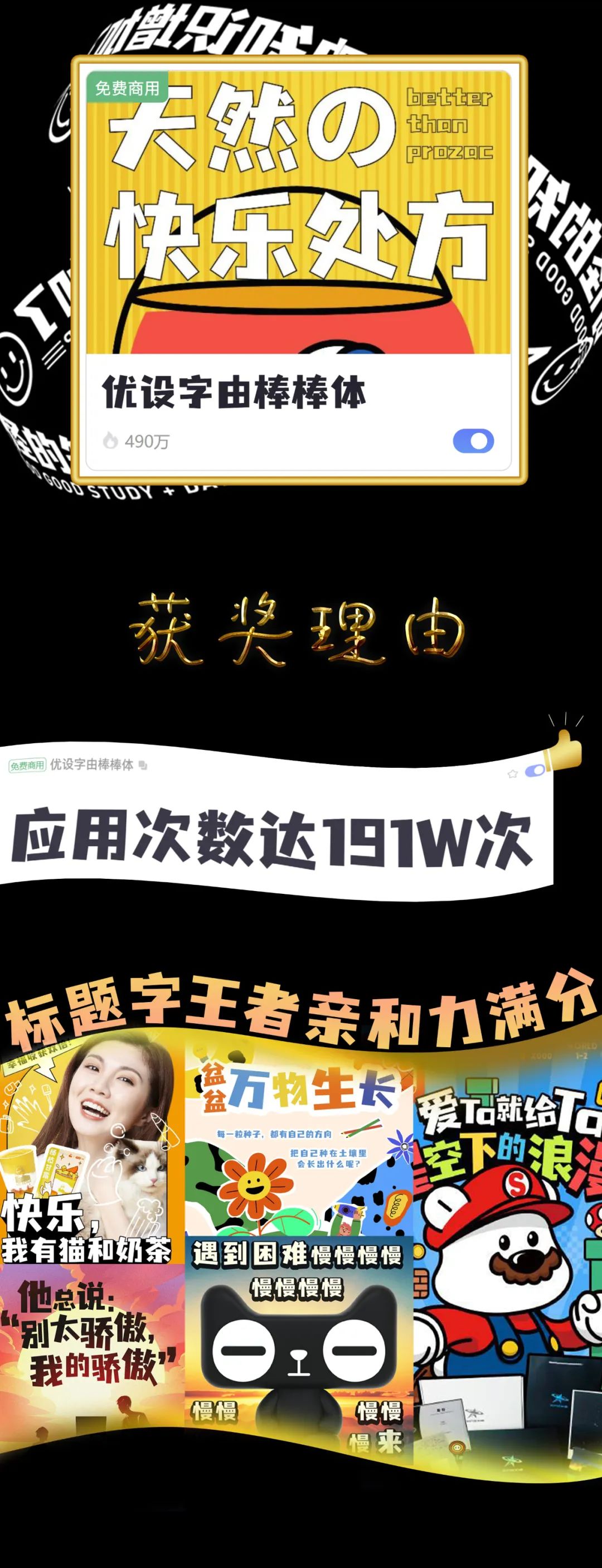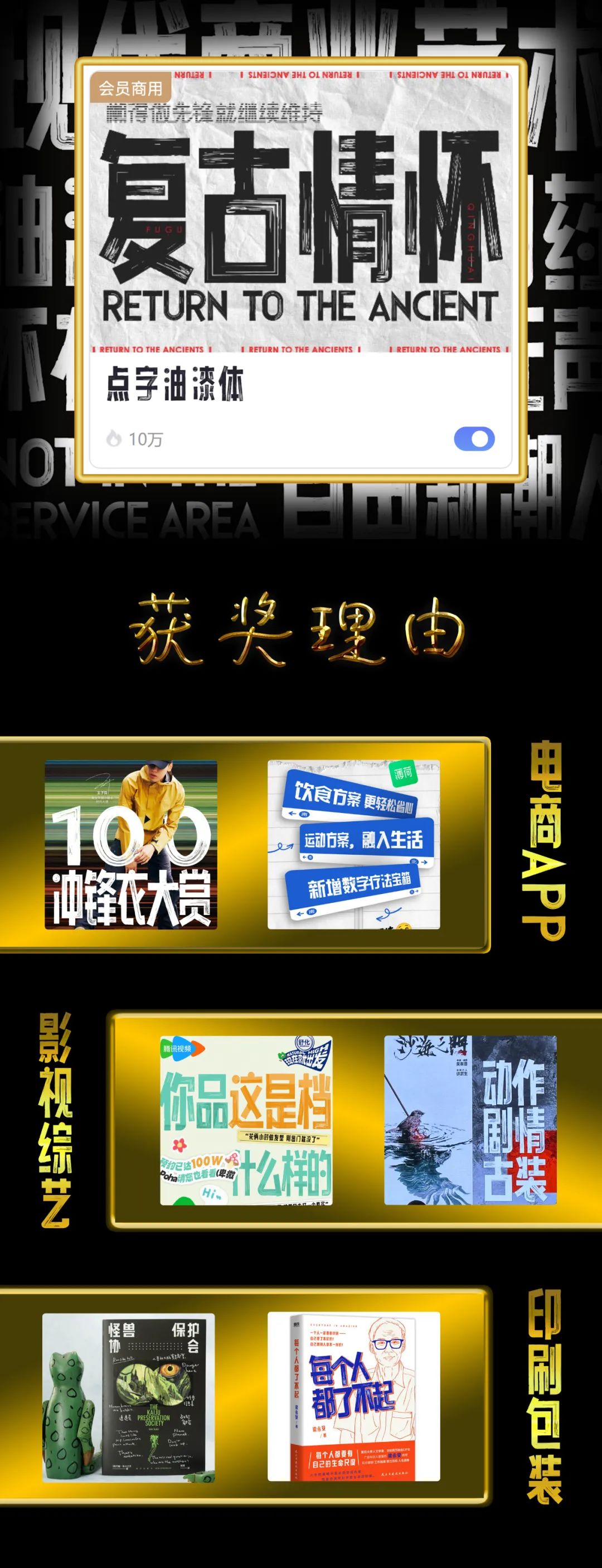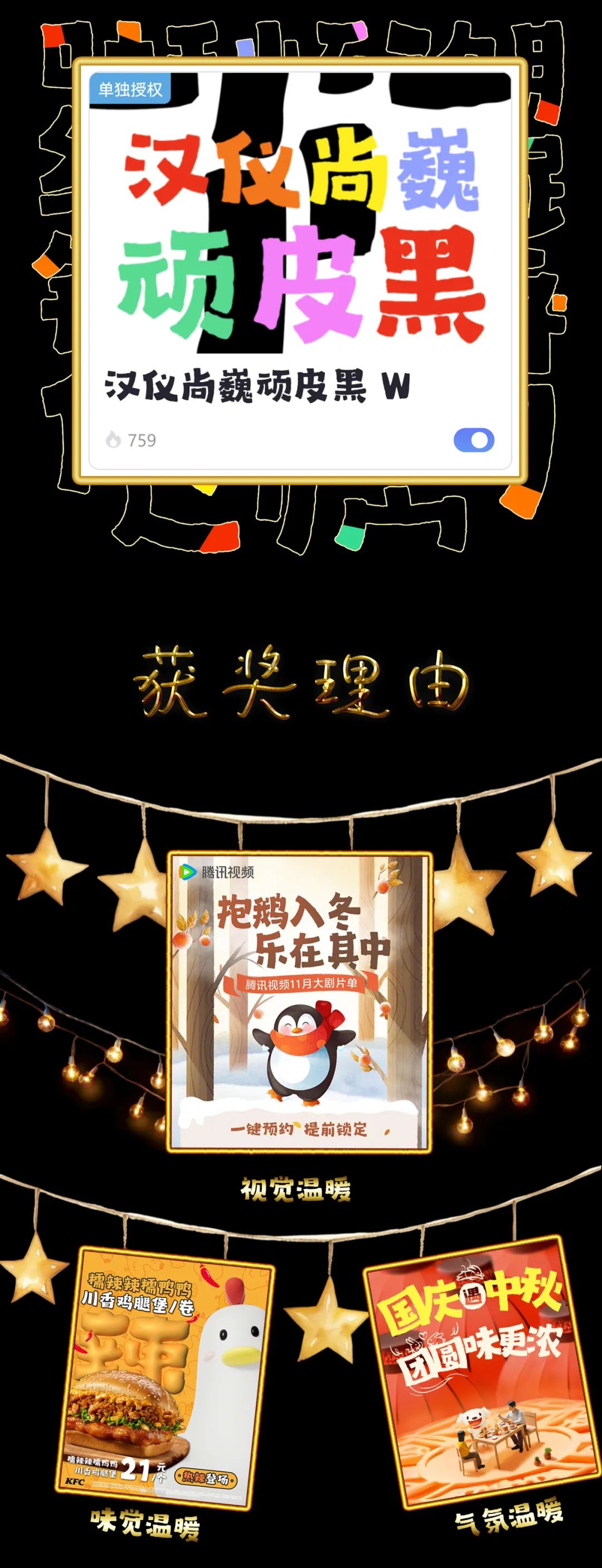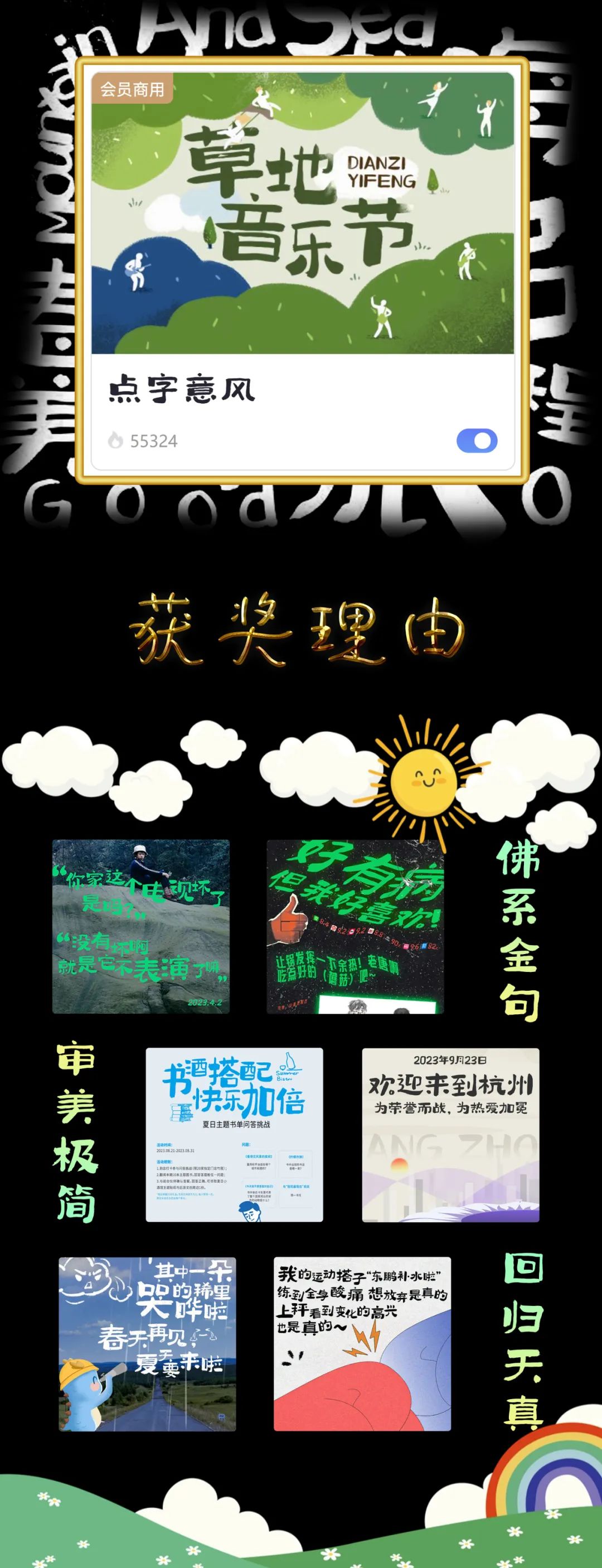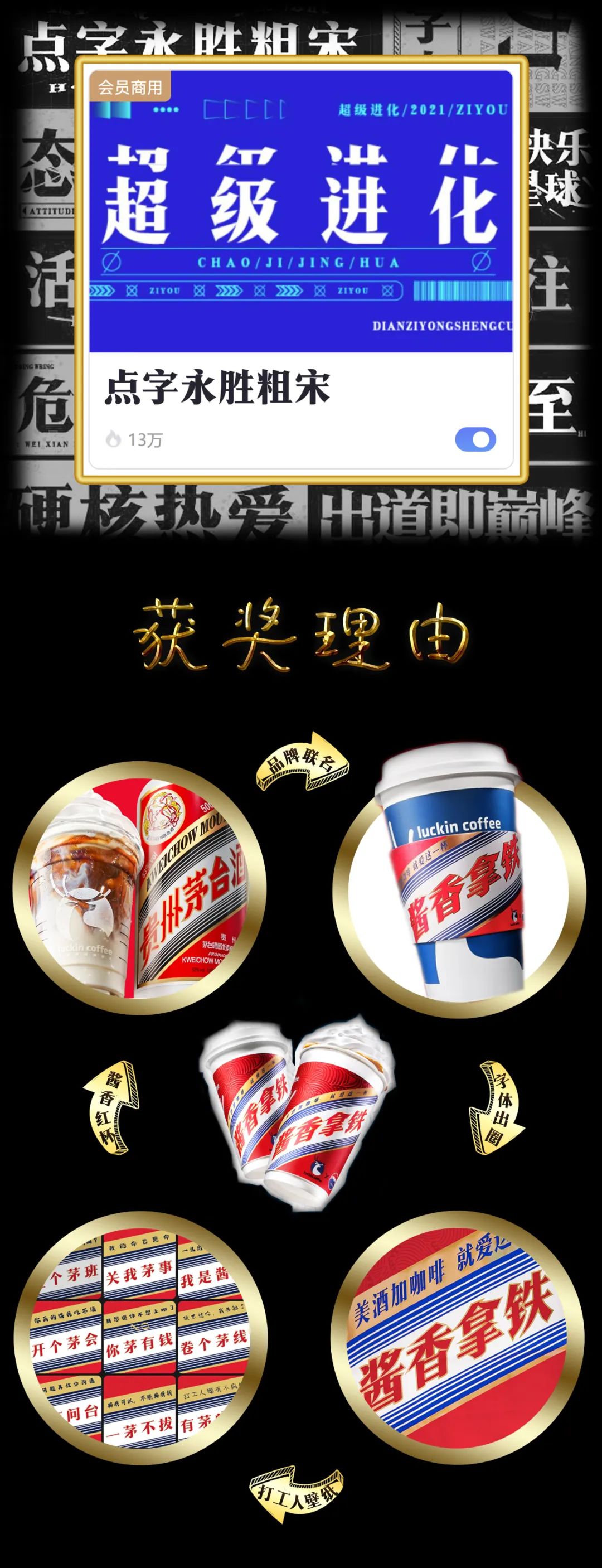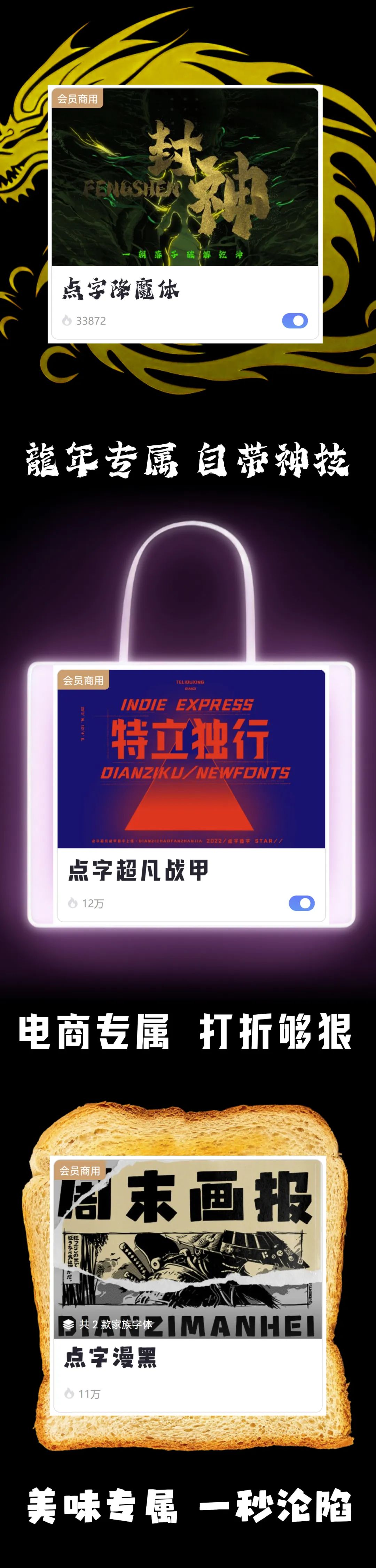
2023字由年度字体出炉,谁是下一个爆款字?
年度最出圈字体
夸夸群又上线了,毕竟今年的点字油漆体实在太抢眼了,几乎是全领域通吃。
年度最受欢迎字体
棒棒体就跟它的名字一样,每年都用得很棒,今年更是高达1919021次应用。
年度最佳联名字体
借着“酱香拿铁”的东风,点字永胜粗宋,今年也摇身一变,成了网红字体。
年度最温暖的字体
今年有一款单独授权的字体比较出圈,经常能在社交媒体中看到,它就是汉仪尚巍顽皮黑。
年度最佛系的字体
卷不动的年轻人,都像意风一样躺平了,字形看起来就很舒适,有一种返璞归真之感。
年度最优雅的字体
得意黑还没上线字由的时候,就已经用在了很多地方,瘦瘦的,带着笑的字体,应该没人会不喜欢吧?
年度最有魅力的字体
每次用苍穹,都能感受到一种拼搏、不服输的内在力量,是一款格局很大的字体。
年度最有潜力的字体
其实会员字中还有很多潜力股,比如“龙行龘龘”的降魔体,“真五折”的超凡战甲,“美味派对”的漫黑,都是2024待爆帝